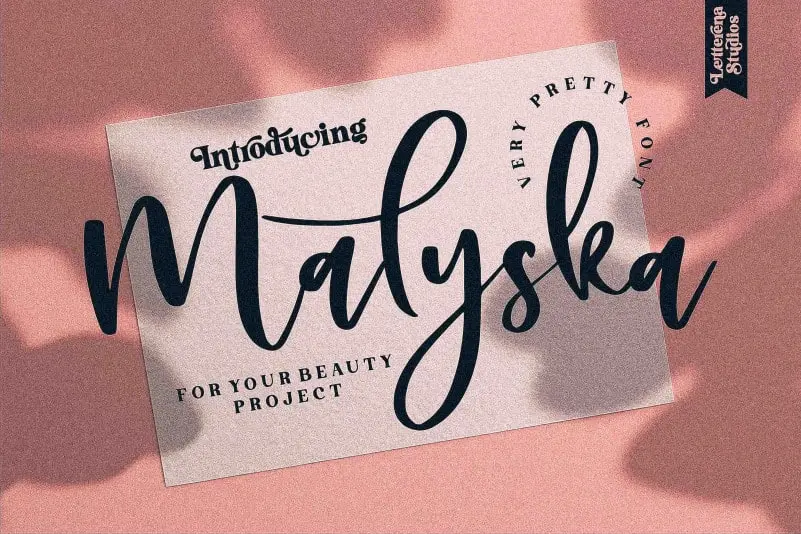
Malyska Calligraphy Font – Download Grátis
A Malyska Calligraphy Font é uma elegante tipografia com traços que parecem dançar no nível base. Inspirada na caligrafia romântica e suave, esta fonte traz um toque casual e sofisticado, perfeita para diversos usos. Seja para criar marcas de logotipos, convites de casamento, cabeçalhos, camisetas, letras no cartão, sinalização, rótulos, notícias, flyers ou até mesmo selos, a Malyska Calligraphy é uma fonte que fará o seu trabalho em qualquer aplicação. Experimente esta fonte e descubra a variedade de possibilidades criativas que ela oferece.